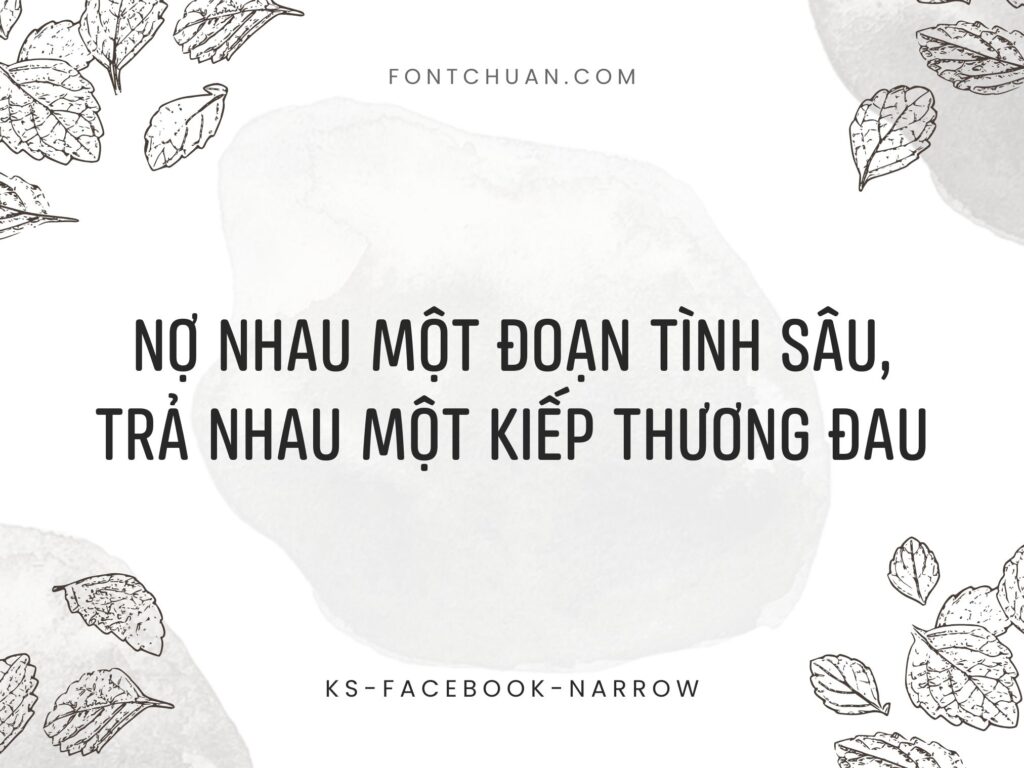
Font Ks Facebook Narrow Việt Hóa
Tác giả Font: Dalton Maag Ltd
Facebook Narrow App là một kiểu chữ sans-serif được thiết kế bởi Dalton Maag Ltd cho thương hiệu Facebook. Với phong cách hẹp, hiện đại và tối ưu cho hiển thị trên màn hình, font này mang đến sự chuyên nghiệp, dễ đọc và tính ứng dụng cao trong nhiều lĩnh vực thiết kế khác nhau. Bên cạnh vai trò là một font thương hiệu, Facebook Narrow App còn được đánh giá là một Font chữ bất động sản phù hợp cho các dự án cần sự tin cậy, gọn gàng và hiện đại — chẳng hạn như trong thiết kế logo công ty, hồ sơ dự án, biển bảng và ấn phẩm quảng bá dự án nhà ở hoặc khu đô thị. Font này hỗ trợ nhiều ngôn ngữ, bao gồm cả tiếng Việt, và được sưu tầm, đăng tải bởi thành viên của Font Chuẩn.
Font có cấu trúc chữ rõ ràng, độ dày nét đồng nhất và các đường nét tinh tế, tạo nên sự cân bằng giữa tính thẩm mỹ và khả năng đọc. Facebook Narrow App phù hợp cho các thiết kế liên quan đến thương hiệu, truyền thông xã hội, tiêu đề và nội dung số. Các ngành nghề như quảng cáo, công nghệ, giáo dục và bất động sản có thể tận dụng hiệu quả font này. Ngoài ra, Facebook Narrow App cũng thích hợp cho các sự kiện như lễ hội, sinh nhật, ngày Nhà giáo và Valentine.